「世界で一番売れてるフォント集」の気になる中身
どれも見逃せないフォントばかりですが、わたしが特に注目するのは次のフォントです。
Futura
Futuraは、幾何学的または線形サンセリフで構成された、もっともよく利用されているフォントのひとつです。ドイツのバウハウス・カルチャーに非常に影響を受けた Futura は、1927年にポール・レナーによって設計されました。誕生してから90年近く、Futura は新鮮であり、デザイナーやタイポグラフィーの間で人気の続く書体と言えます。
URW Din
デジタルオンラインフォント、DIN 1451 Fette EngschriftとFette MittelschriftはURWによって1984年に作られました。そしてこれらは全てのDIN書体の基礎となりました。両方のタイプフェースはURW SINUS システムのためにデザインされ、主に道路標識のサインのために使用されました。Futuraに並んで人気の高いフォントのひとつで、フォント名の「Din」とは「ドイツ工業規格」の事で、もともとは道路標識やマンホールなどに使われていた万能書体。48ウェイトが揃い、Webフォントにも対応しています。セミコンデンスでそれが面白いDIN書体の特徴となっています。タイポグラフィとして非常に幅広い使い方ができます。ウェブやアプリ、e-Bookなどに最適です。
こちらもデザイナーなら持っておきたいフォント「Din」。一見シンプルでありふれたフォントに見えますが、細部までこだわり抜かれた設計になっています。一度使い始めたら、その良さを実感することでしょう。
Trend、Trend Rough、Trend Handmade
ファッションやグラフィックなど世界のデザイントレンドに対応した書体で、ここではハンドメイドスタイルや、グランジの質感を表現したスタイルな全3バージョン、総額5万円分のフォントが揃います。
3バージョンのフォントがあらかじめ用意されているLatinotype社のTrend。わざわざPhotoshopなどで加工しなくてもいいので楽ちんです。デザインプロジェクトの内容にあわせて、どれを使うか自由に選んでくださいね。
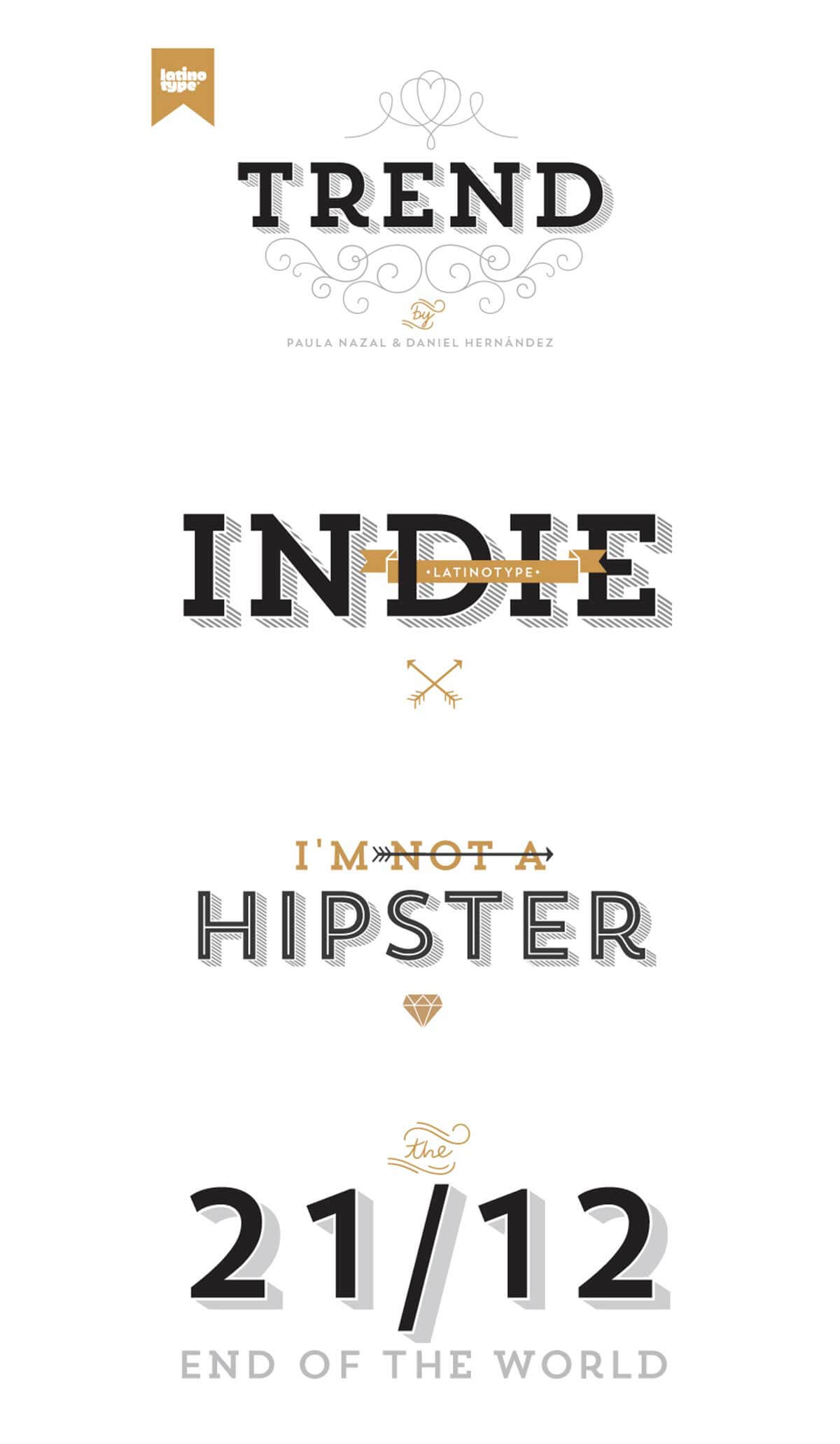
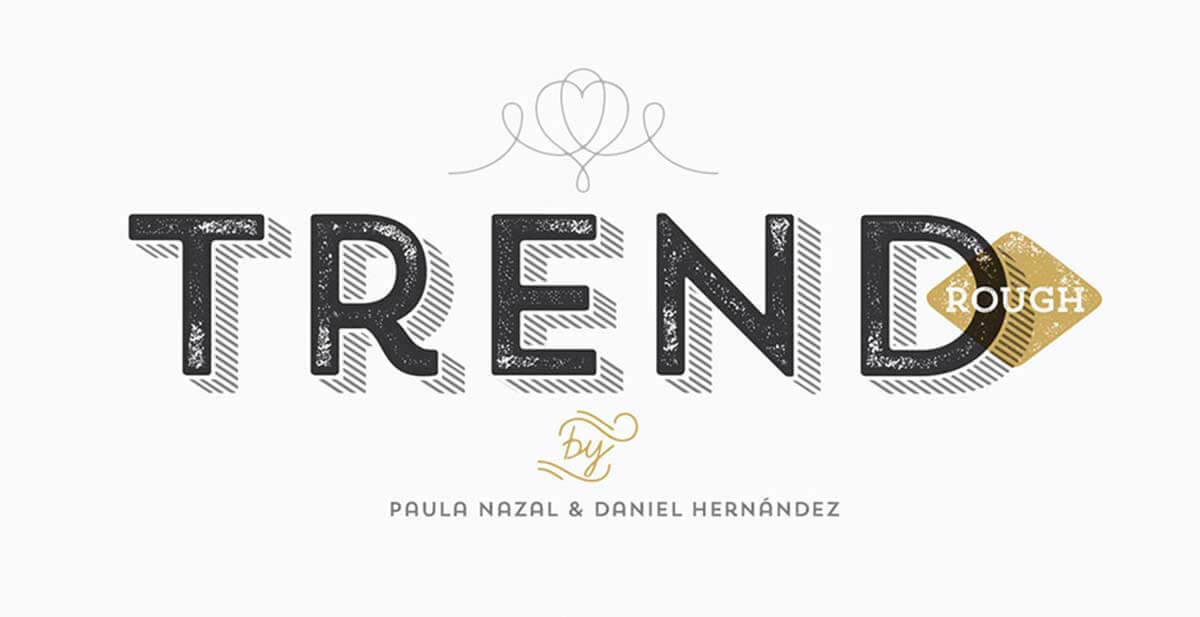
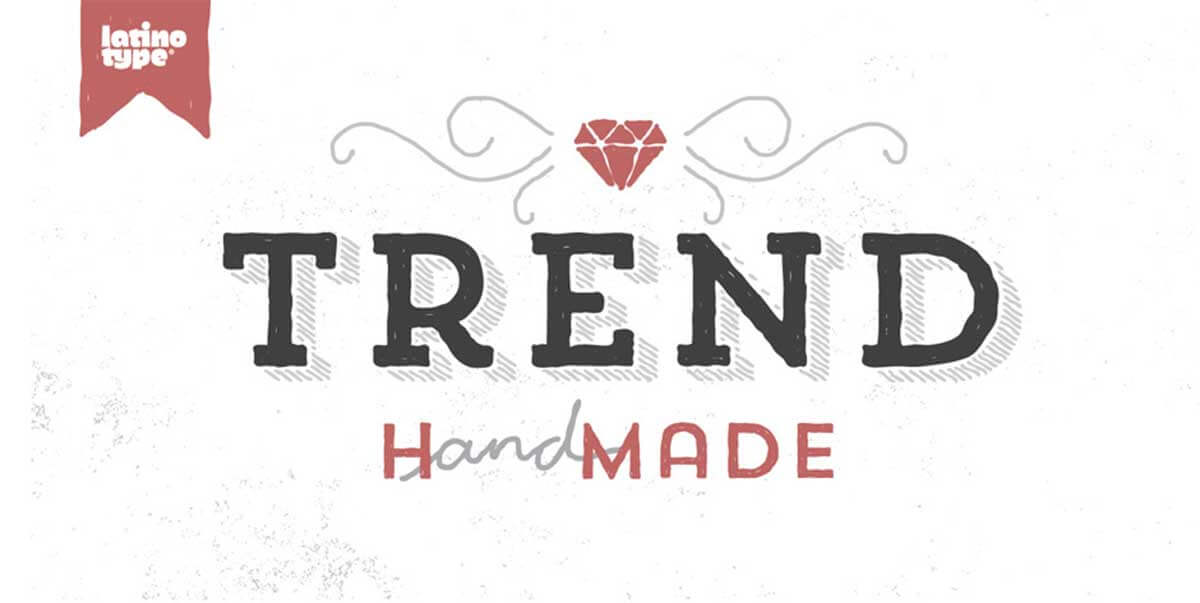
Adorn – Complete Family
20種類のさまざまなビンテージフォントを網羅したお買い得な書体セットで、フォントを組み合わせて使うだけでプロ顔負けのデザインを作成できます。
たくさんついてくる飾りとフォントを組み合わせるだけで、ヴィンテージ風のロゴが完成してしまうすごいキット。時間はないけどデザインの完成度を高めたいときなどに、役立つこと間違いなしです。
Cera (6 font sample pack)
幾何学スタイルのプレミアムフォントで、読みやすさと可読性ばっちりのスタイルは汎用性の高いサンセリフ書体。
いくつあっても困らないのが、見出しにも小さい文字の長文にも使えるサンセリフフォントのCera。読みやすくウェイトも揃っているので、幅広いデザインプロジェクトに対応できますよ。